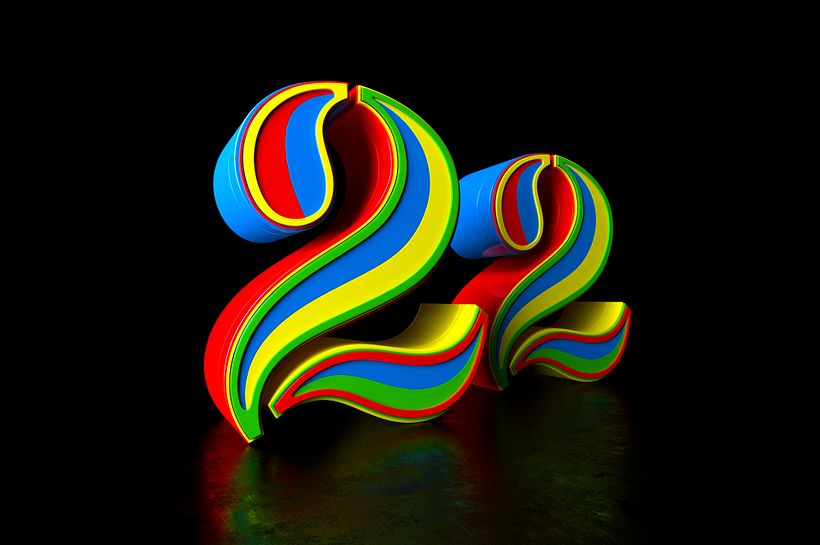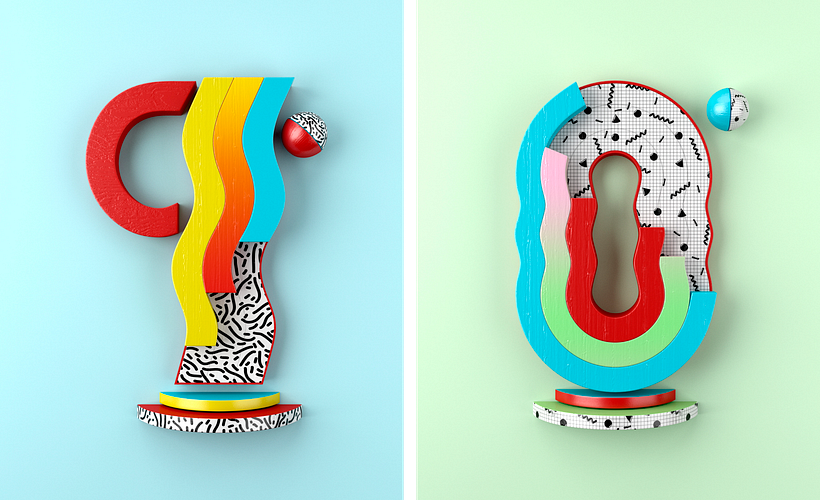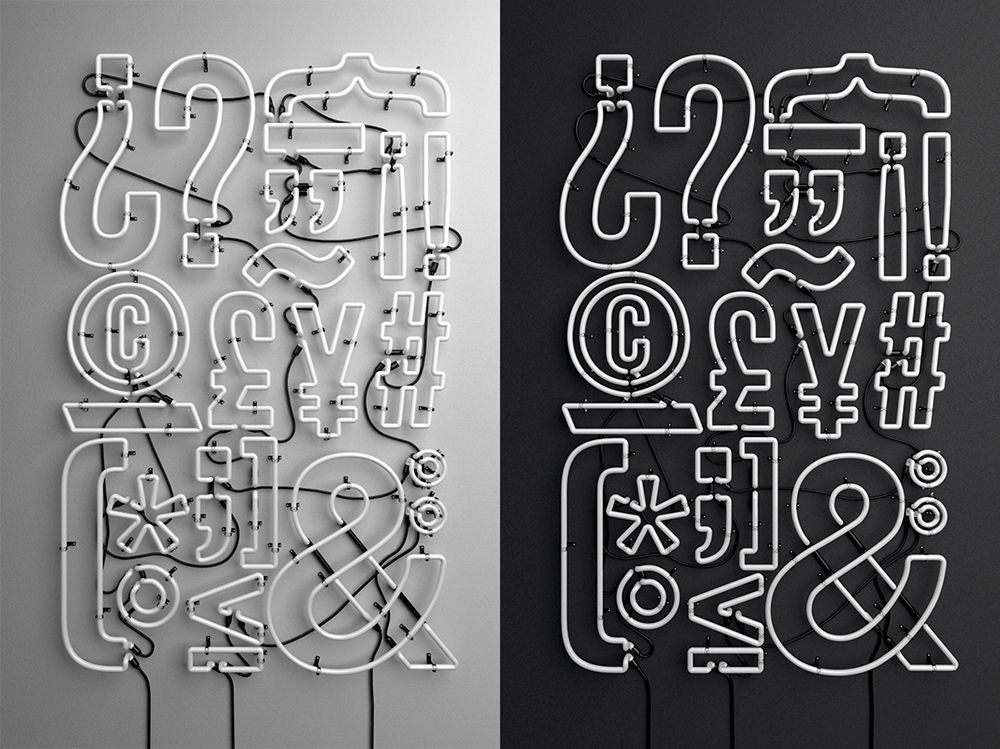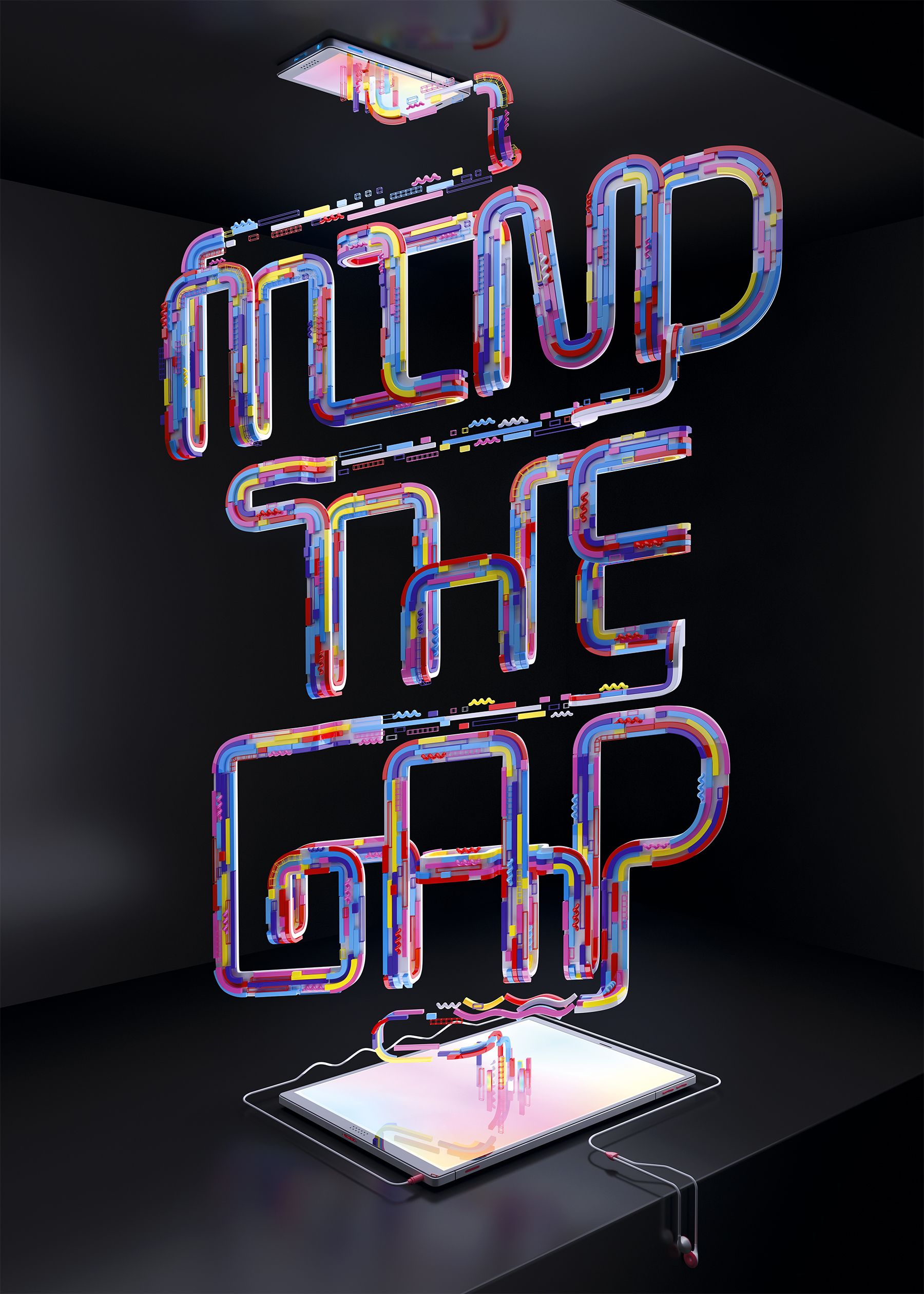
Muokka y su tipografía a todo volumen
Alejandro López Becerro, mejor conocido como Muokkaa, es un diseñador gráfico español que después de estar trabajando en un estudio local de diseño, decidió mudarse a Madrid y emprender su carrera como diseñador e ilustrador 3D.
Gracias a eso ha desarrollado un estilo particular explotando las posibilidades que ofrece la tipografía combinada con la magia del 3D logrando un estilo único lleno de formas, colores y figuras.
Muokka y su tipografía a todo volumen  1
Muokka estudió Diseño Gráfico en la Escuela de Artes de Salamanca y ha trabajado para clientes como The Oprah Magazine, Fortune, Field and Stream, Wired Alemania, Die Zeit, Yorokobu, AIGA, Directv, Heineken y Refinery29.
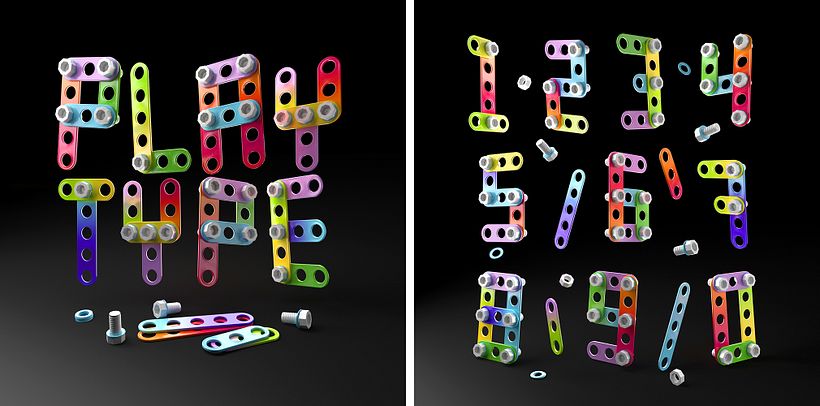
Muokka y su tipografía a todo volumen  3
Muokka y su tipografía a todo volumen  4
Muokka y su tipografía a todo volumen  5
El trabajo de Muokka sin duda es una exploración creativa a través de la tipografía, el 3D y sobre todo el color y las texturas.
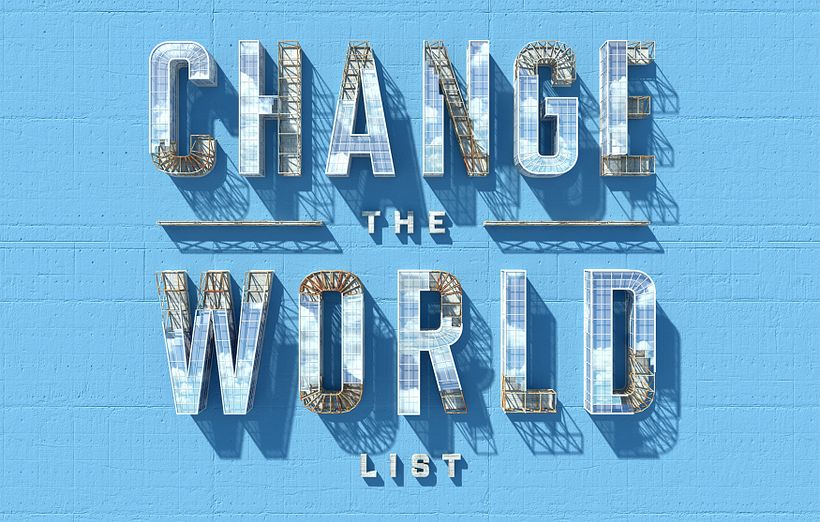
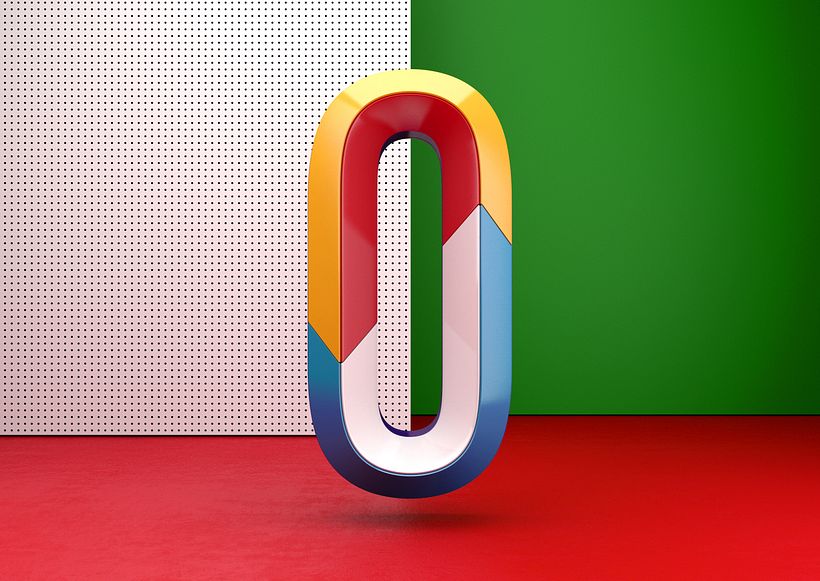Muokka y su tipografía a todo volumen  7
Muokka y su tipografía a todo volumen  8
Muokka y su tipografía a todo volumen  9
Muokka y su tipografía a todo volumen  10